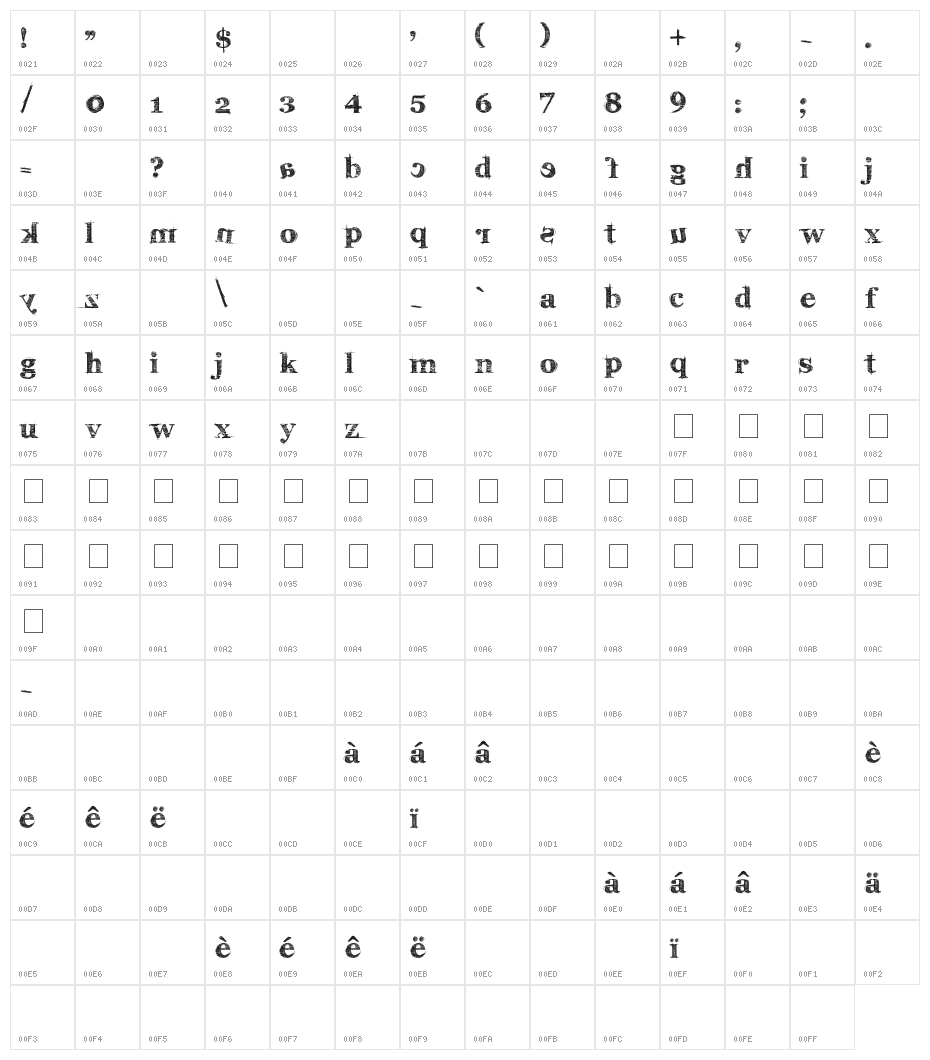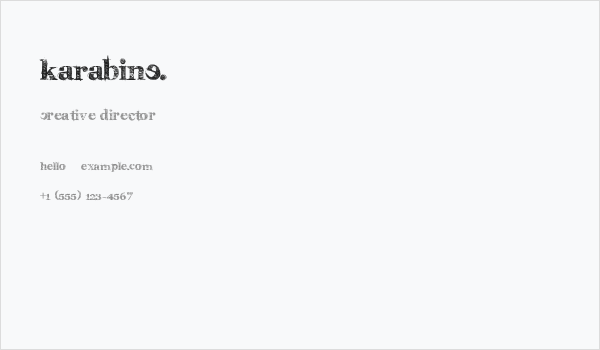
karabinE. Font
| Progetti proposti | Perfect for vintage posters, album covers, branding for rustic-themed businesses, or any design needing a bold, textured look. |